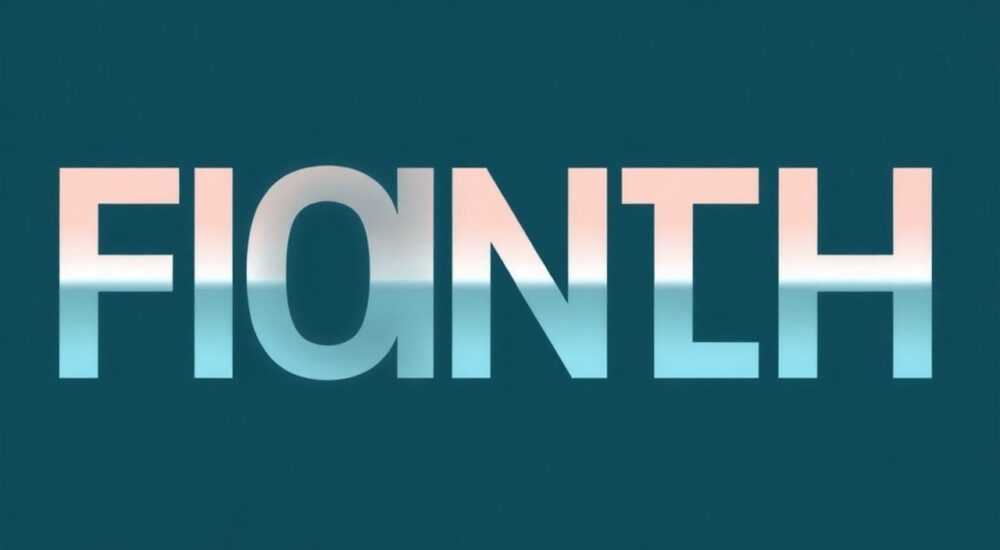
Как сделать красивый шрифт в фотошопе
Красивый шрифт в Photoshop — это не просто выбор гарнитуры, а комплексный подход, включающий типографику, цвет, текстуру, эффекты и композицию. Чтобы достичь профессионального результата, важно понимать, как сочетать стили, настройки и инструменты программы. Главное правило: красота рождается в деталях — от кернинга до тени.
Выбор подходящего шрифта: основа визуальной гармонии
Первый шаг к созданию красивого текста — правильный выбор шрифта. Не каждый шрифт подойдёт для любого проекта. Например, рукописные или декоративные шрифты отлично работают в свадебных приглашениях или постах о моде, но будут выглядеть нелепо в деловом отчёте. Основные категории шрифтов включают засечковые, беззасечковые, рукописные, моноширинные и декоративные.
При выборе шрифта ориентируйтесь на цель дизайна. Если вы создаёте логотип бренда, подумайте о его долгосрочном восприятии. Шрифт должен быть легко читаемым даже в мелком размере и хорошо масштабироваться. Для цифровых платформ предпочтительны беззасечковые шрифты — они четко читаются на экранах.
Не стоит использовать более двух разных шрифтов в одном проекте. Это может вызвать визуальный хаос. Лучше комбинировать начертания одного семейства — например, светлое и полужирное. Такой подход обеспечивает единство стиля и профессиональный вид.
Как выбрать шрифт по настроению
Каждый шрифт передаёт определённую эмоцию. Засечковые (например, Georgia, Times New Roman) ассоциируются с классикой, доверием, серьёзностью. Беззасечковые (Helvetica, Arial) — с минимализмом, современностью и технологичностью. Рукописные шрифты (Brush Script, Pacifico) вызывают ощущение теплоты, индивидуальности и творчества.
- Для брендинга: выбирайте уникальные, запоминающиеся шрифты с хорошей читаемостью.
- Для рекламы: акцентируйтесь на контрастных, крупных шрифтах с высокой узнаваемостью.
- Для соцсетей: допустимы игривые, декоративные стили, особенно если целевая аудитория — молодёжь.
Тип шрифта |
Где использовать |
Примеры |
Засечковые |
Печатные издания, корпоративные документы |
Times New Roman, Garamond |
Беззасечковые |
Веб-дизайн, мобильные приложения, презентации |
Roboto, Montserrat, Open Sans |
Рукописные |
Приглашения, логотипы, посты в Instagram |
Great Vibes, Dancing Script |
Декоративные |
Афиши, заголовки, логотипы |
Bebas Neue, Impact |
Работа с текстом в Photoshop: ключевые инструменты и параметры
Photoshop предоставляет мощный набор инструментов для работы с текстом. Основной — это инструмент «Текст» (T), который позволяет добавлять горизонтальные и вертикальные надписи. После ввода текста откройте панель «Свойства» (Window → Properties), где можно настроить все параметры: размер, гарнитуру, интерлиньяж, кернинг, трекинг и выравнивание.
Особое внимание уделите интерлиньяжу (межстрочному интервалу). Слишком плотные строки трудно читать, особенно в длинных абзацах. Оптимальный интерлиньяж — 1.2–1.5 от размера шрифта. Например, для 16 pt подойдёт интерлиньяж 19–24 pt.
Кернинг (интервал между парами символов) влияет на визуальную плотность текста. Photoshop предлагает автоматический кернинг (Metrics или Optical), но вручную его можно корректировать для достижения идеального баланса. Особенно важно это при работе с заглавными буквами или логотипами.
Шаги создания текста в Photoshop
- Нажмите T для активации инструмента Текст.
- Щёлкните на холсте и введите нужный текст.
- В панели свойств выберите шрифт, размер и цвет.
- Настройте интерлиньяж, кернинг и выравнивание.
- При необходимости преобразуйте текст в контуры (правый клик → «Создать контуры»), чтобы применять векторные операции.
Эффекты слоя для красивого шрифта: тени, обводка, наклон и объем
Эффекты слоя — главный инструмент для придания тексту глубины и стиля. Откройте их через двойной клик по слою с текстом или через меню «Слой → Стиль слоя». Вот основные эффекты, которые стоит освоить:
- Тень (Drop Shadow) — добавляет объём, отделяет текст от фона. Настройте угол, расстояние, размытие и непрозрачность.
- Внутренняя тень (Inner Shadow) — создаёт эффект углубления, часто используется в кнопках и 3D-тексте.
- Обводка (Stroke) — контур вокруг букв. Можно задать положение (внутри, по центру, снаружи), цвет и толщину.
- Наложение градиента (Gradient Overlay) — покрывает текст градиентом, что особенно эффектно с крупными заголовками.